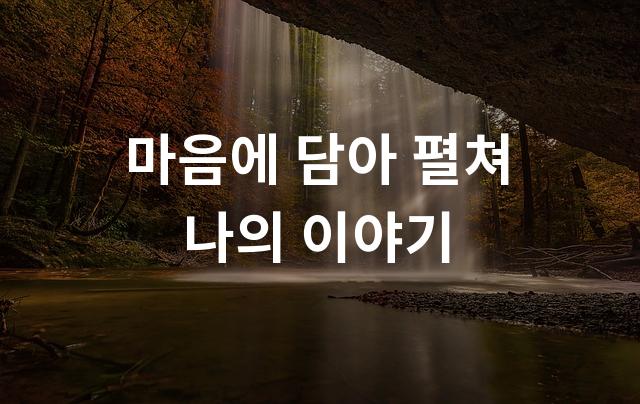
스포카 한 산스 네오는 현대적 감각의 기본 고딕 폰트로, 깔끔하고 선명한 라인이 특징입니다. 디지털 환경에서의 가독성을 높이기 위해 설계되었으며, 감성적으로는 심플하고 명확한 메시지 전달에 최적화되어 있습니다.
스포카 한 산스 네오은(는)
기본 고딕, 감성적인, 부드러움 계열의 생김새를 가지고 있으며
웹/앱 디자인, 디지털 광고, 보고서/문서 등에서 자주 활용되며, 효과적인 메시지 전달에 적합합니다.
이 폰트는 광고/마케팅, 기술/IT, 금융/비즈니스 분야에 잘 어울리며,
현대적, 명확한, 전문적인 느낌을 담고 있는 것이 특징입니다.